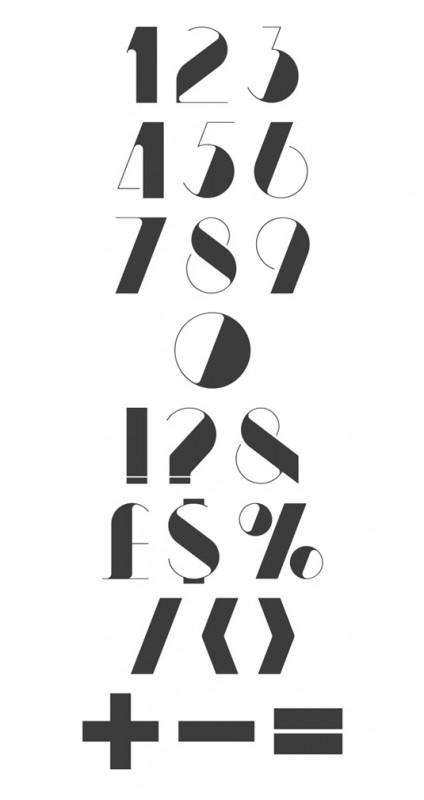
Nuovo appuntamento con il font del giorno. Oggi voglio condividere con te un carattere unico, originale e molto forte, dalla comunicazione diretta e chiara: Kaiju Font! Se sei alla ricerca di un carattere tipografico molto accattivante e che riesca ad arrivare in modo netto e diretto al tuo utente, dai un’occhiata a questo free font.
Kaiju
Ecco il nostro font del giorno. Kaiju Font un carattere semplice, leggibile e perfetto per scopi editoriali. Font elegante, originale e molto accattivante che riesce a dare forza alla nostra comunicazione su una pagina web o un progetto di print design, adattabile ad uno stile flat ma anche a un design più audace e aggressivo. Questo carattere è stato sviluppato dal designer Anthony James che ci regala questo font in maniera gratuita sia per usi commerciali che personali.